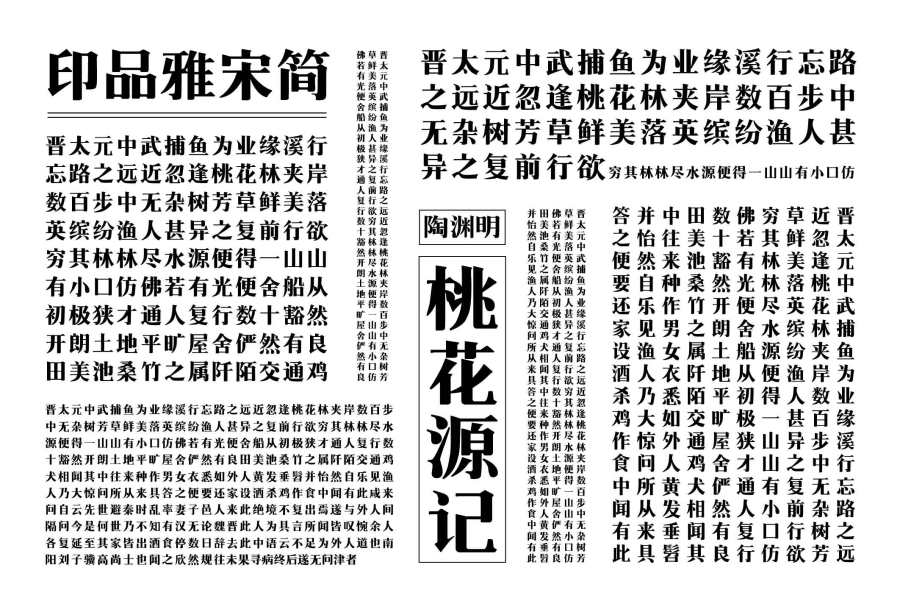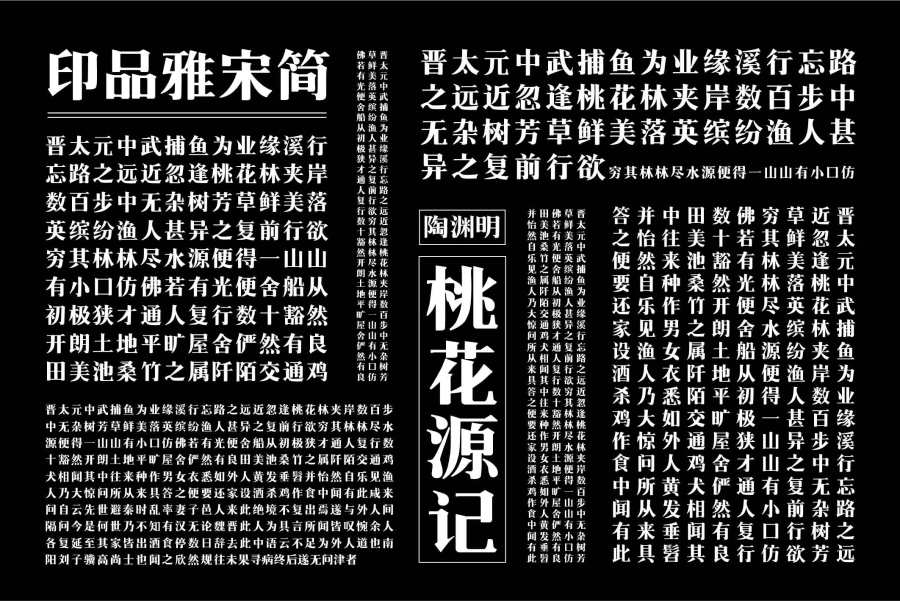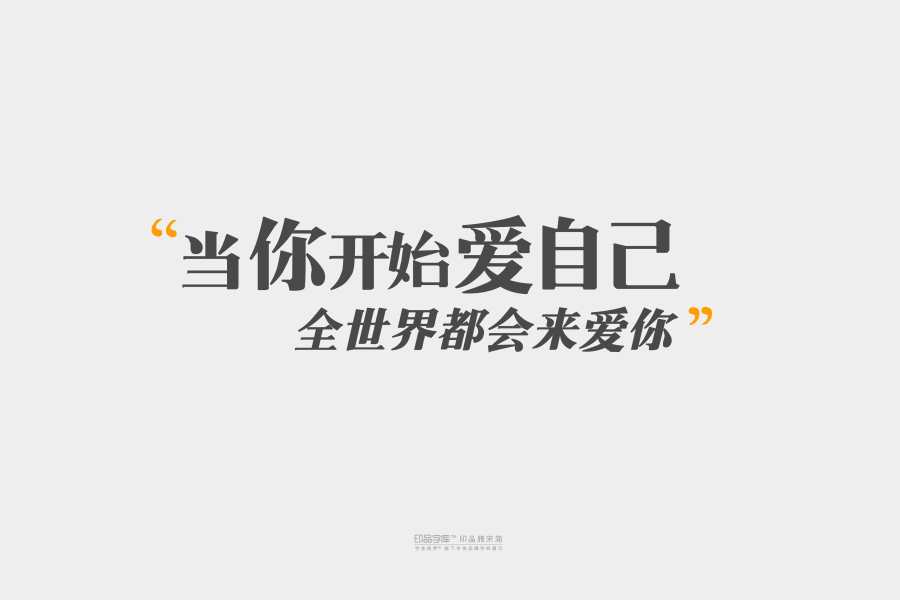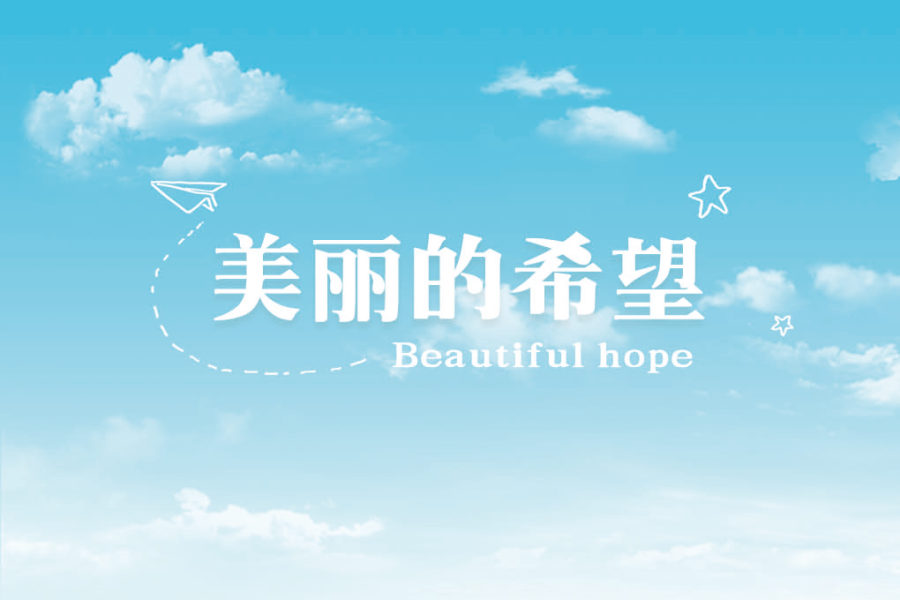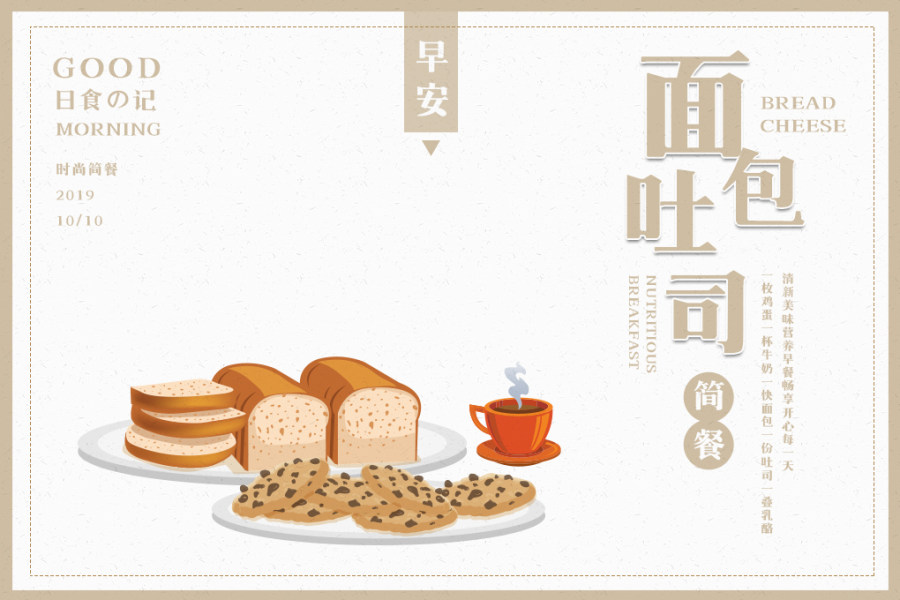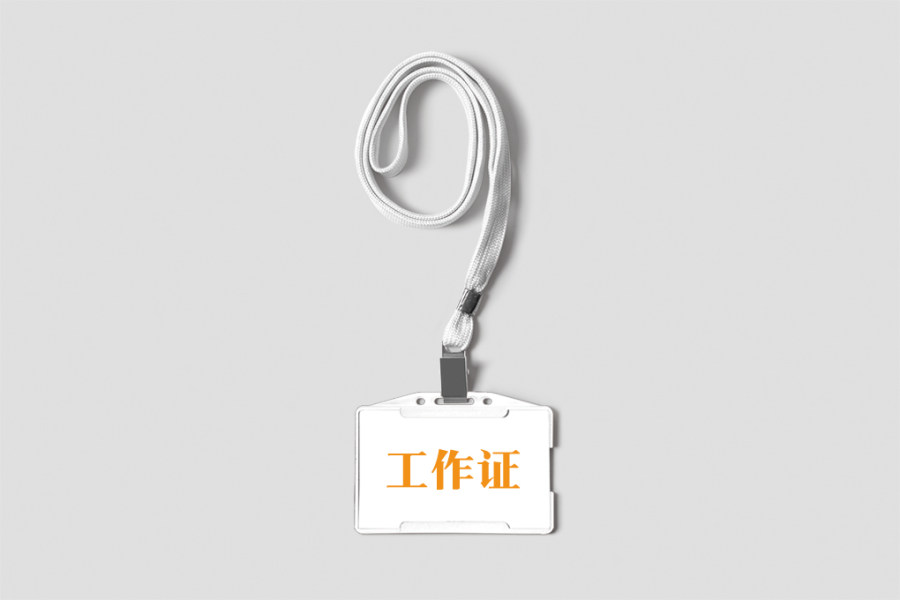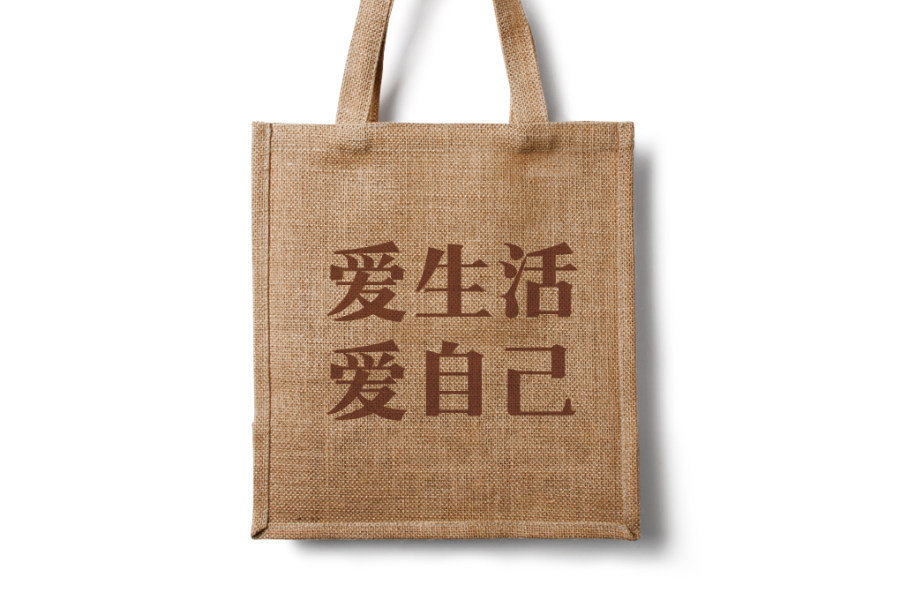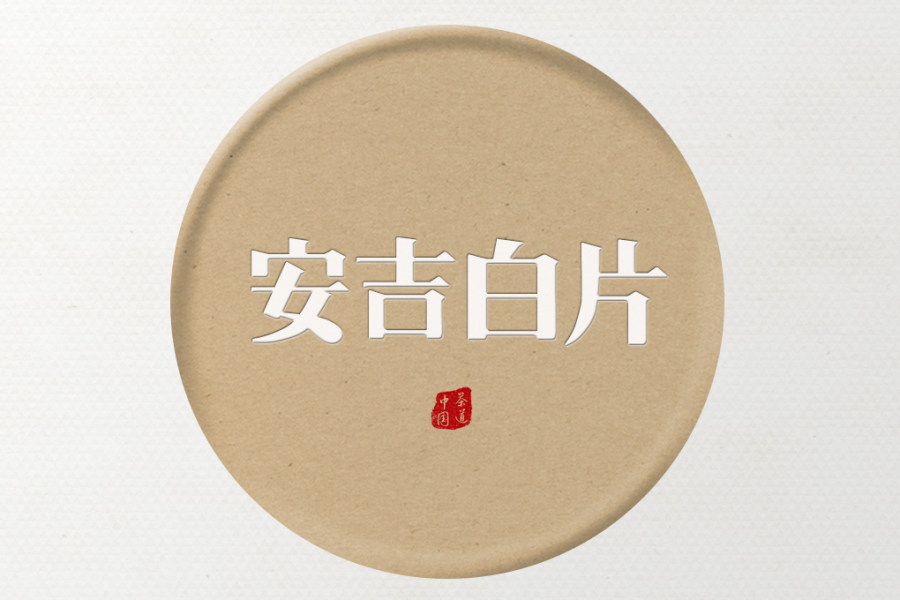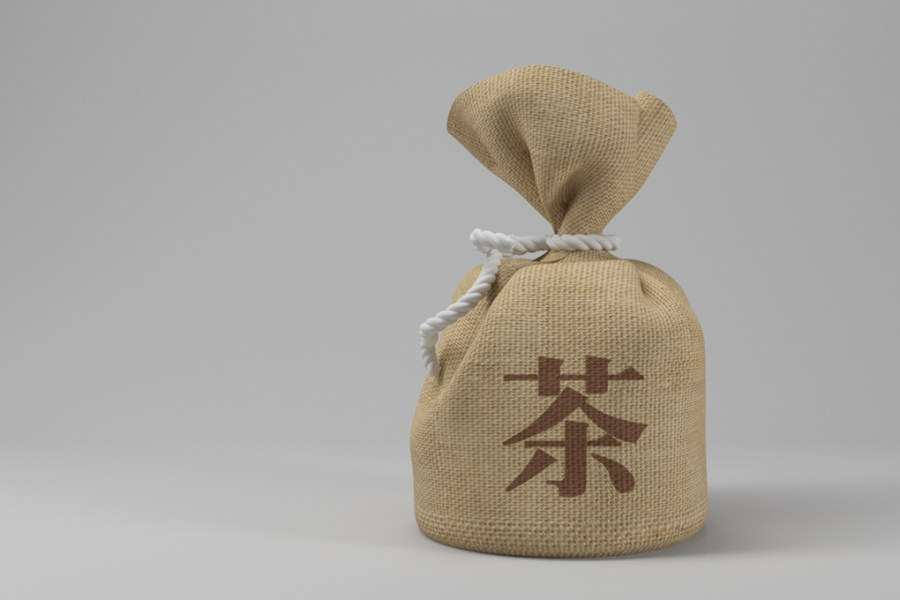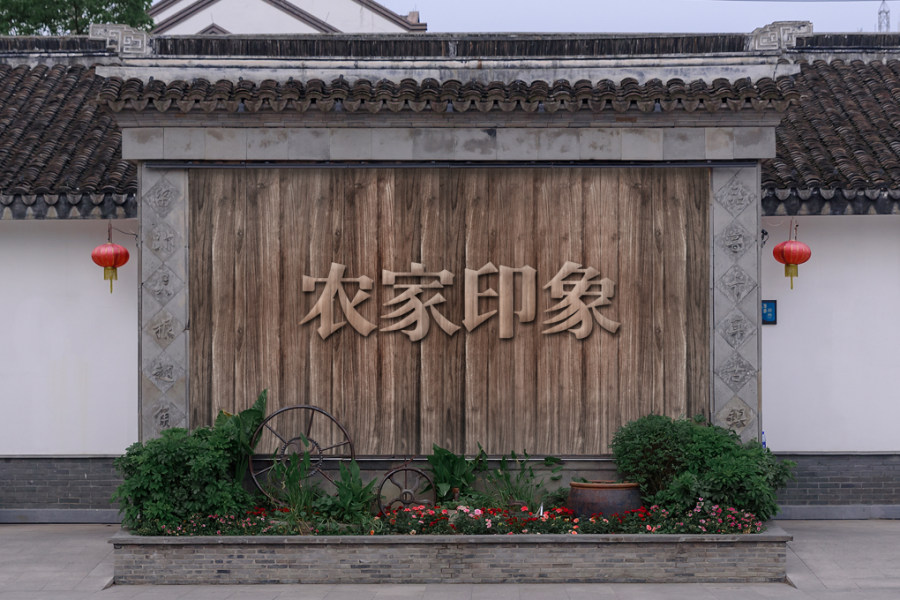
印品雅宋简 中黑
印品雅宋简字体线条流畅顺滑,平整耐看,棱角柔滑,装饰角的圆滑处理,使整款字体看起来既不缺少正式感又能增添个性,字体浑厚有力十分耐看,整体庄重,结实,端正大气,适......
• 字体源于“生活”,故事源于“生活”,“生活”与“生活”的结合铸就了一款有故事的字体。
在做印品雅宋简这款字体设计之前,设计师翻阅了许多关于宋体的资料,从古至今宋体多用于各类文章的正文排版,自然少不了正式感,那么,如何在不减少正式感的情况下又能增添一些个性的小细节进去呢?设计师开始了自己的思考,于是把将宋体原有的尖端,都改成了圆润平滑的角,变成这款字体的装饰部分,让整款字体看起来既不缺少正式感又能增添个性的感觉。这样的调整让整款字体显得自然且耐看,又不失端正,正式的感觉。不同于印品清版宋字体,这款印品雅宋简字重稍粗适用于各类文章标题,封面。